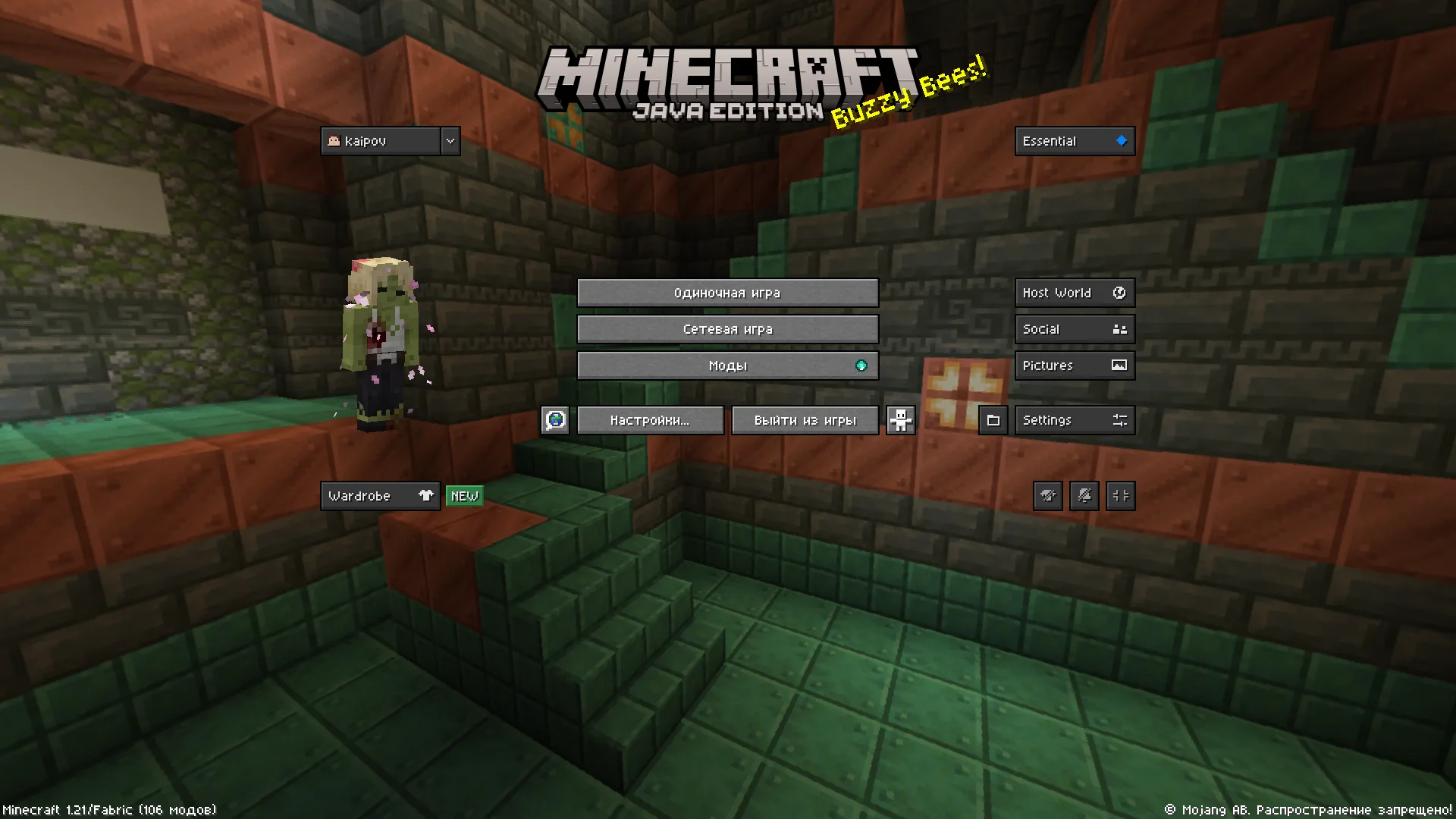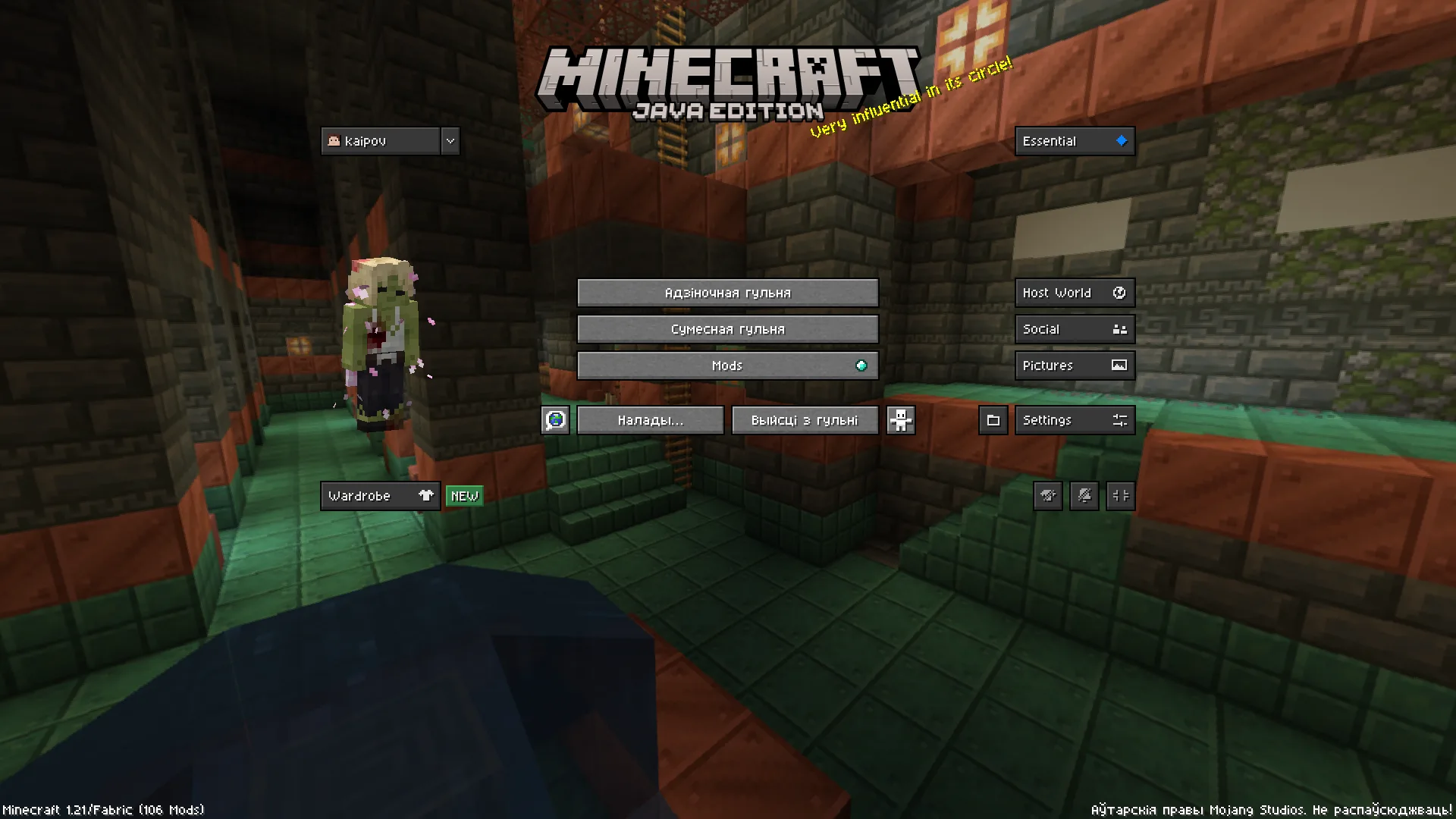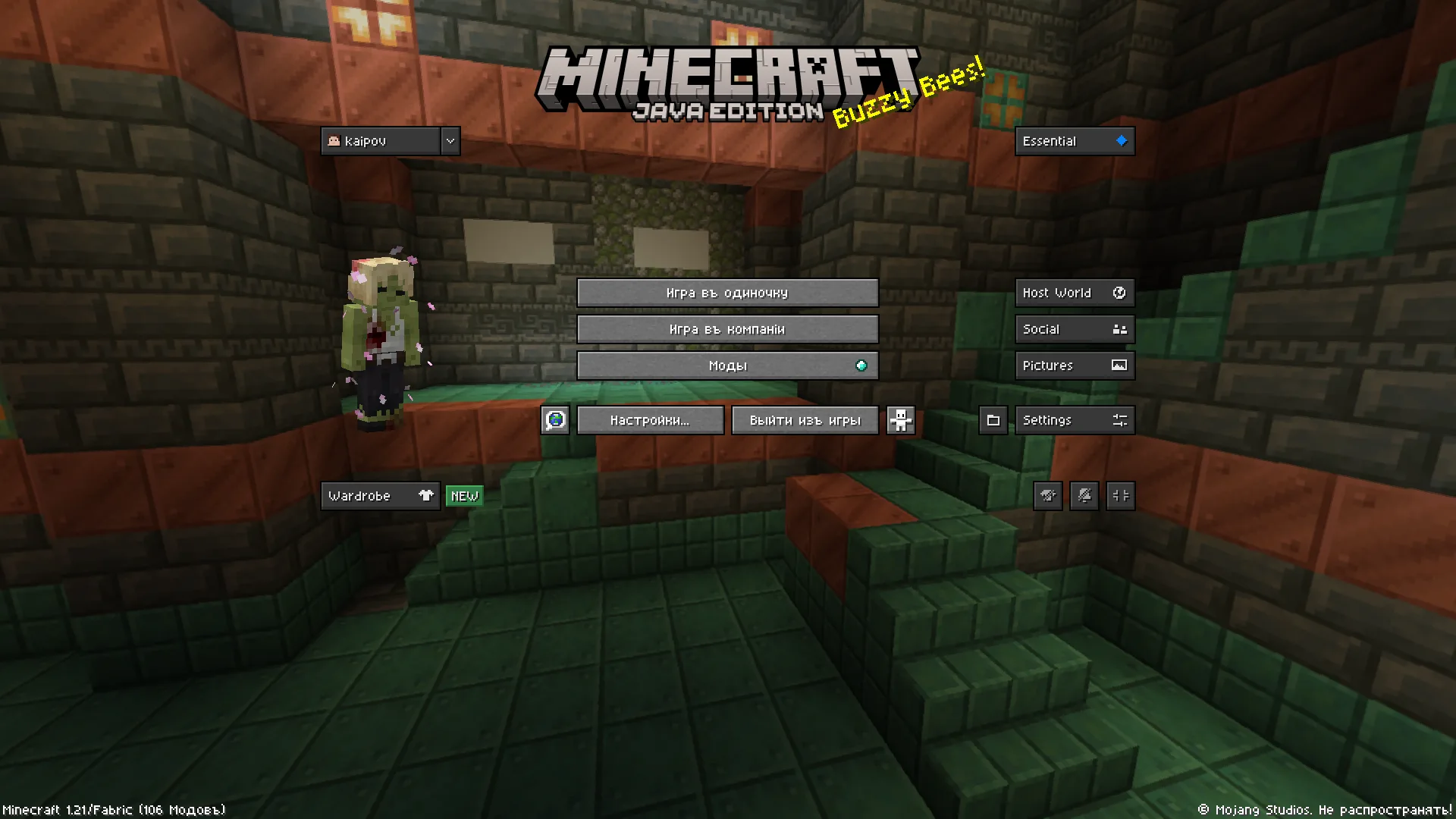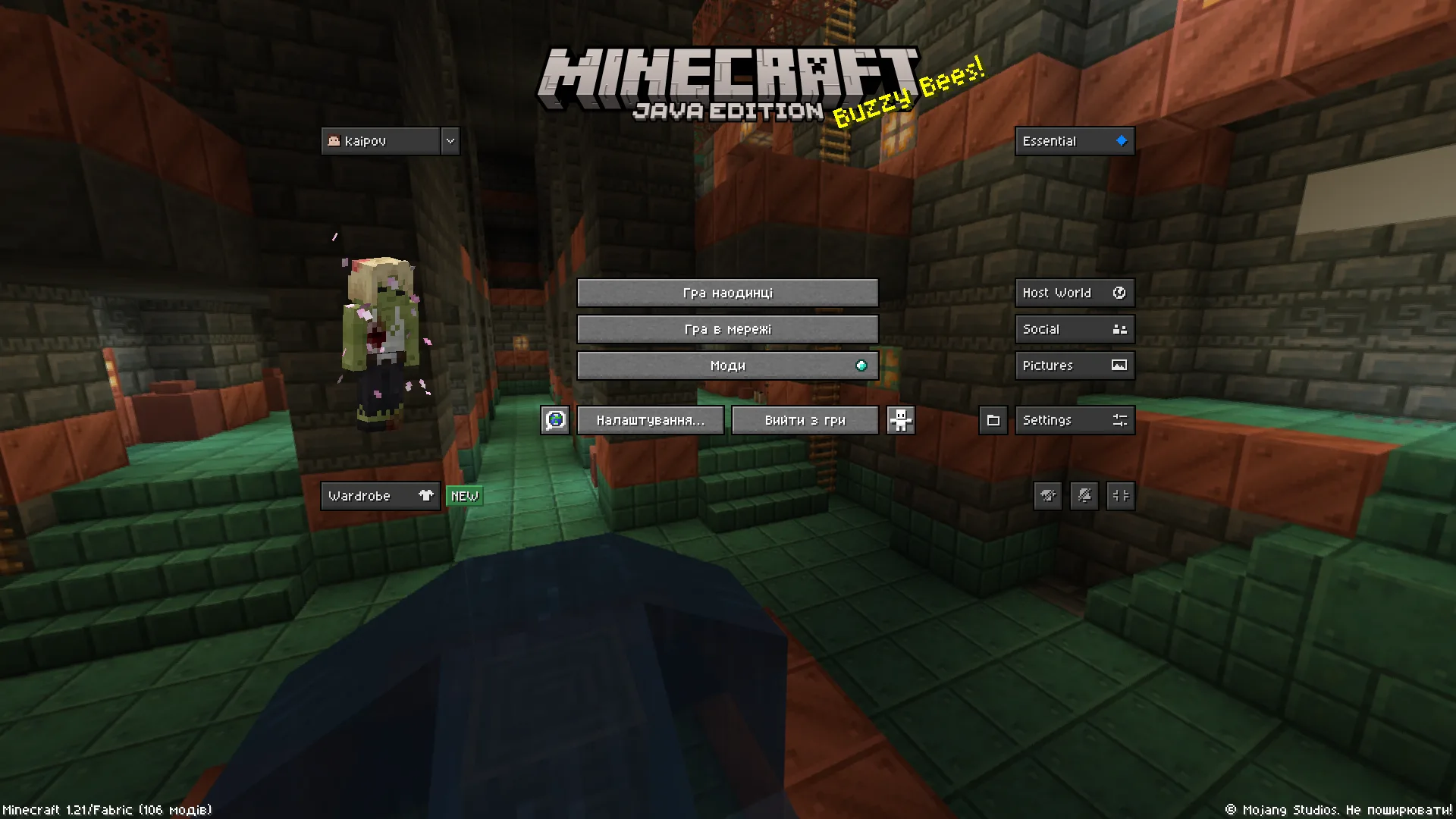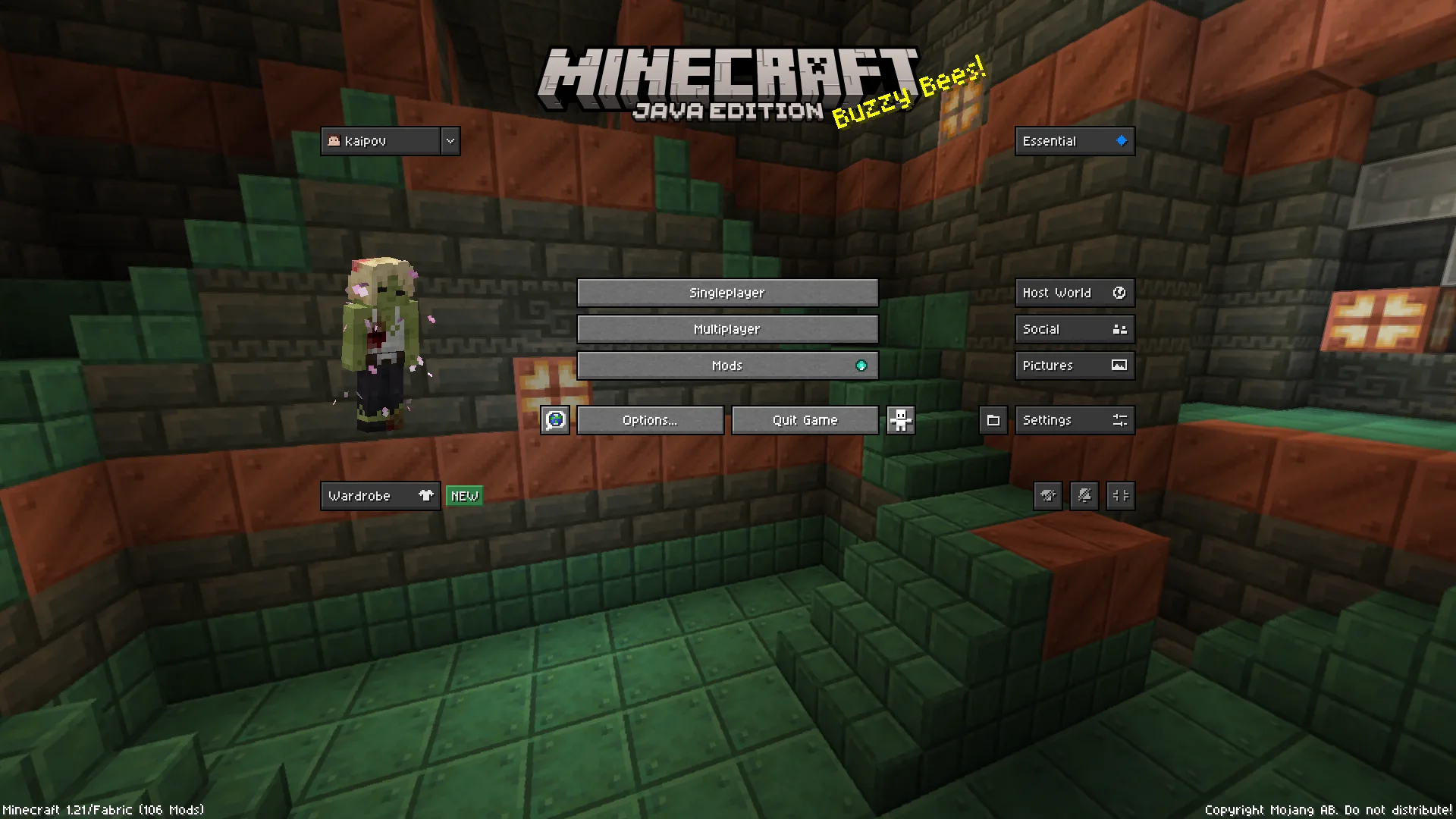
Aseprite Fonts
Добавляет полноценный рабочий шрифт из Aseprite в Minecraft. Ресурспак поддерживает кириллицу, включая русский, украинский и белорусский языки.
Этот ресурспак добавляет в Minecraft полноценный рабочий шрифт из программы Aseprite — пиксельного графического редактора. Шрифт перенесён напрямую из редактора, сохраняя свой оригинальный стиль и атмосферу.
Ресурспак поддерживает кириллические алфавиты, включая русский, украинский, белорусский языки, а также дореформенную русскую орфографию. Совместимость охватывает широкий диапазон версий Minecraft, обеспечивая стабильную работу.